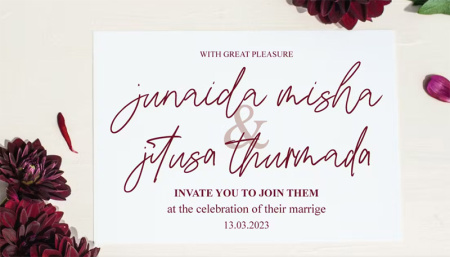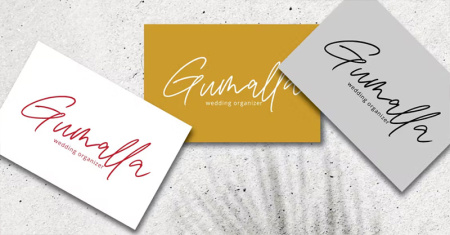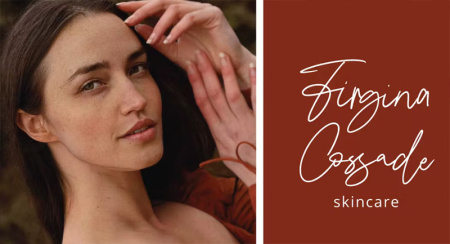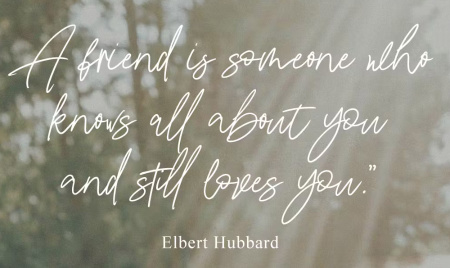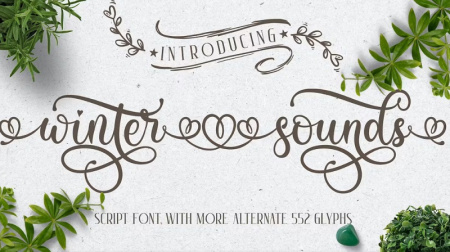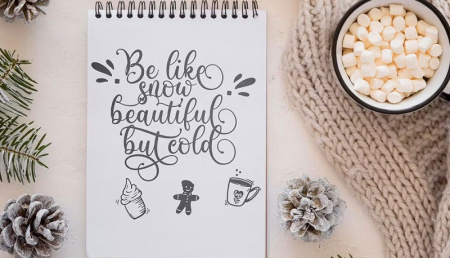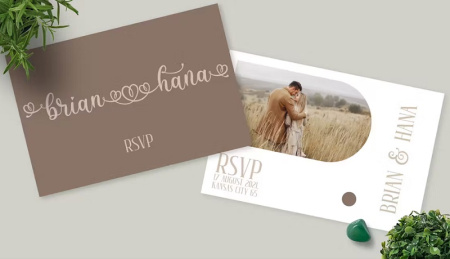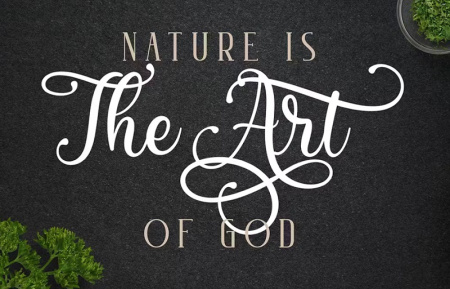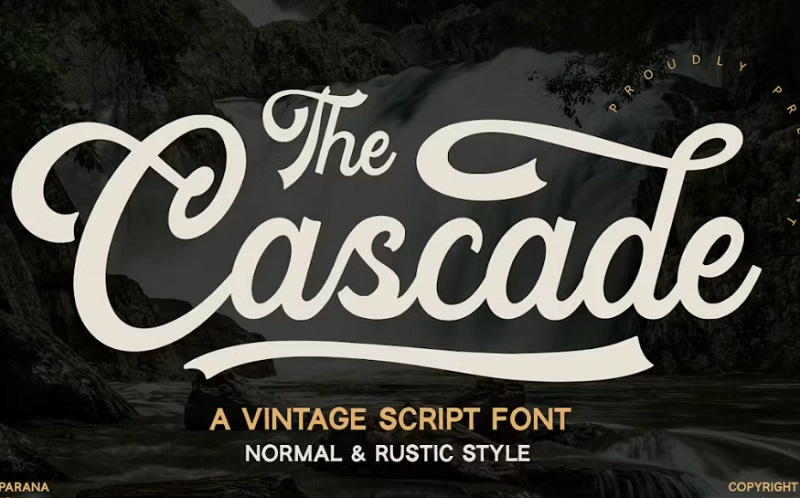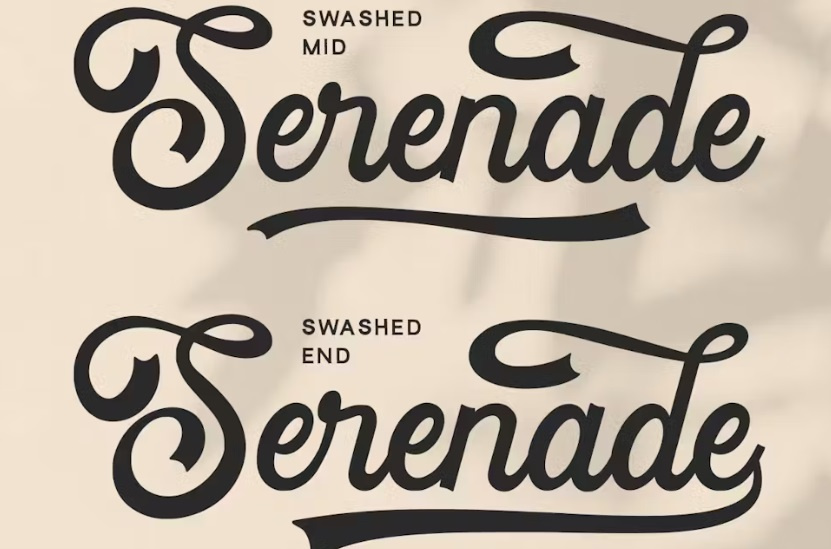
فونت انگلیسی کشیده شامل مجموعه ای از فونت های زیبای کشیده با سبک دست نویس و کاراکتر های تزئینی می باشد! این فونت ها کاربردهای زیادی از جمله: فونت انگلیسی کشیده برای اینشات ، بسیار زیبا در طراحی کارت دعوت، طراحی نام تجاری، کارت ویزیت، نقل قول، پوستر، و غیره دارد. می توان با استفاده از برنامه های هوشمند Open Type مانند Adobe Illustrator، Adobe InDesign، Adobe Photoshop Corel Draw X و Microsoft Word آنها را مشاهده کرد. برای دانلود فونت انگلیسی کشیده از جی اف ایکس دانلود به ادامه مطلب مراجعه کنید.
1- دانلود فونت انگلیسی کشیده زیبا Bathire Signature
فونت انگلیسی کشیده Bathire Signature یک فونت انگلیسی زیبا به سبک دست نویس و امضا است. همچنین می توانید برای تولید تیزر ها و کلیپ های عاشقانه و فانتزی، طراحی لوگو و ... از این فونت استفاده نمایید.
2- فونت انگلیسی زیبا کشیده
این فونت انگلیسی زیبا کشیده با نام Winter Sounds مناسب برای محصولات مختلف مانند دعوتنامه، کریسمس، روز ولنتاین، بستهبندی محصول، نقل قول، طراحی محصول، عکاسی، واترمارک، لوگو، برندسازی و سایر پروژههای عاشقانه می باشد. با استفاده از نرم افزارهایی که از Opentype پشتیبانی می کنند، مانند Adobe Indesign، Adobe CS Illustrator، Adobe Photoshop CC و Corel Draw، می توان به همه موارد آن دسترسی داشت.
3- فونت کشیده نویس انگلیسی
Cascade یک فونت اسکریپت به سبک قدیمی با حس و حال کلاسیک است. فونت کشیده نویس انگلیسی شامل فرمت های otf-ttf-woff و حروف بزرگ و کوچک، اعداد و علائم نگارشی می باشد.
4- دانلود فونت انگلیسی کشیده برای فتوشاپ
Long Path یک فونت انگلیسی کشیده برای فتوشاپ است که برای طراحی و ادیت عکس و فیلم می توانید از آن استفاده کنید. این فونت به راحتی در فتوشاپ و سایر برنامه های گرافیکی قابل اجرا است.